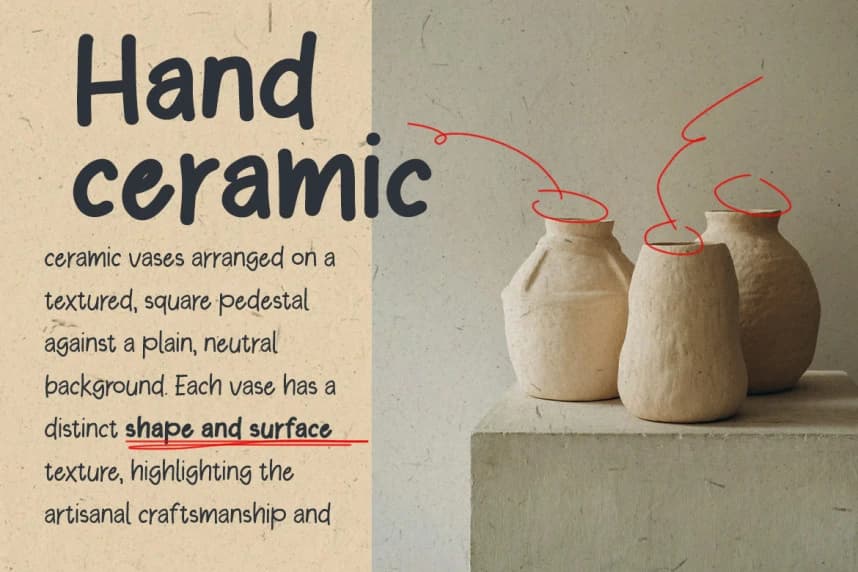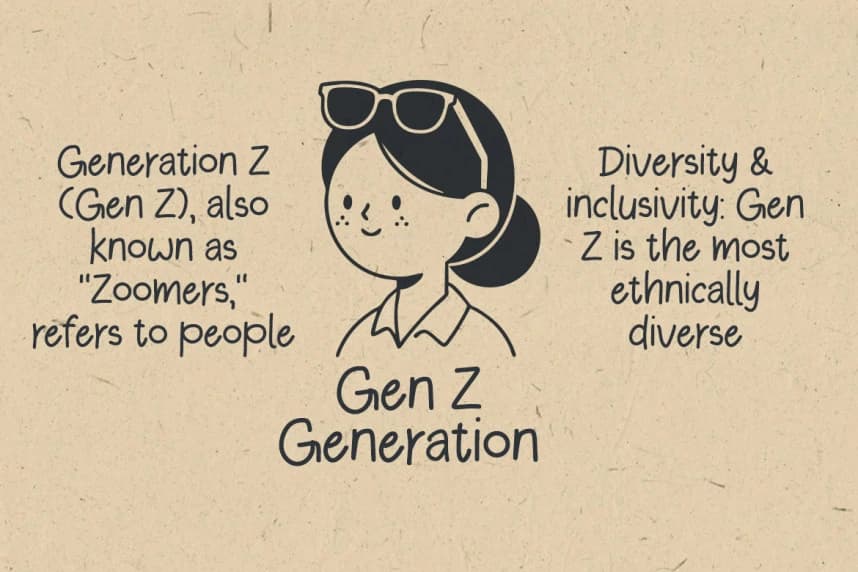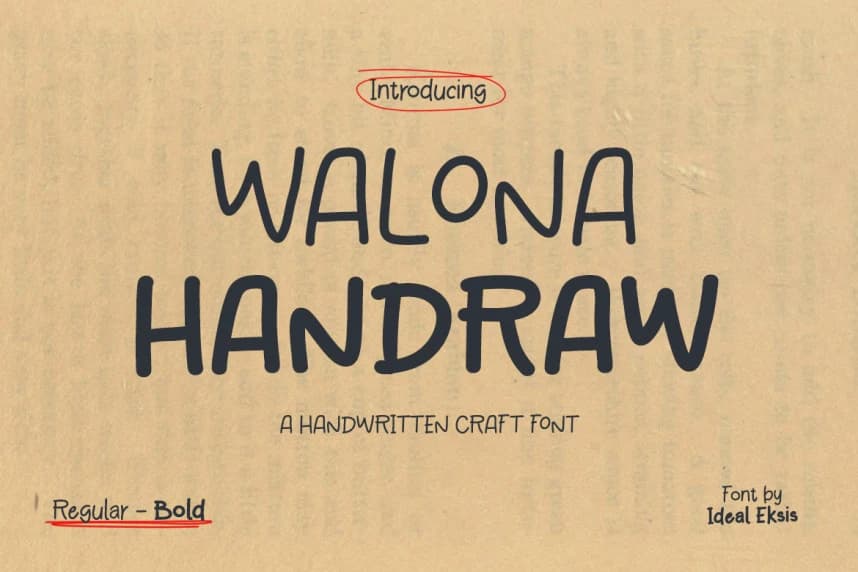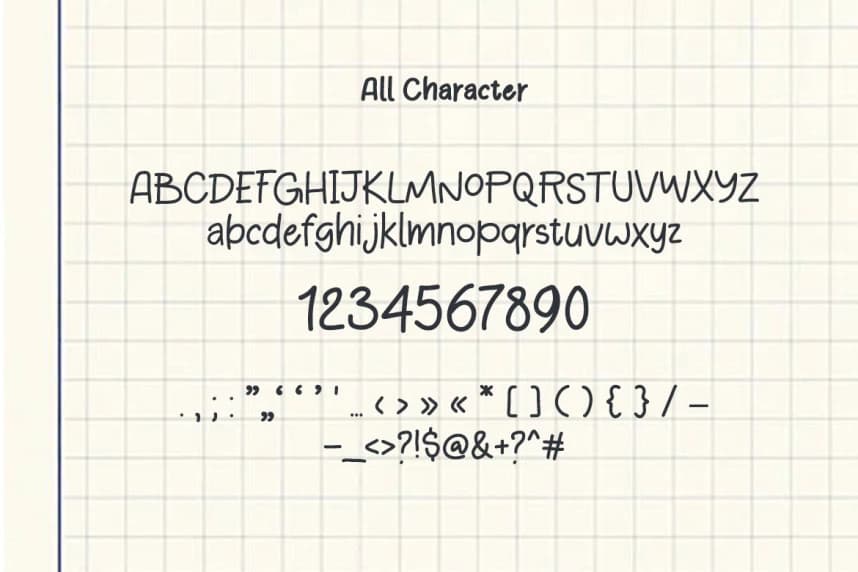
Walona Handraw Font
Walona Handraw Font - Bu yazı tipi, el çizimi görünümüne sahip çekici ve organik bir estetik sunar. Harf biçimleri, orta ile ağır kalınlıkta tutarlı bir ağırlık sergiler ve yumuşak, yuvarlak uçları dostane ve ulaşılabilir bir his uyandırır. Çizgileri ise biraz düzensizdir.
Walona Handraw Font - Bu yazı tipi, el yazısı görünümüne sahip olmasıyla karakterize edilen çekici, organik bir estetiğe sahiptir. Harf biçimleri, tutarlı bir orta-yoğun ağırlığa sahiptir ve yumuşak, yuvarlak uçlarla dostça ve ulaşılabilir bir his verir. Vuruşlar hafifçe düzensizdir.